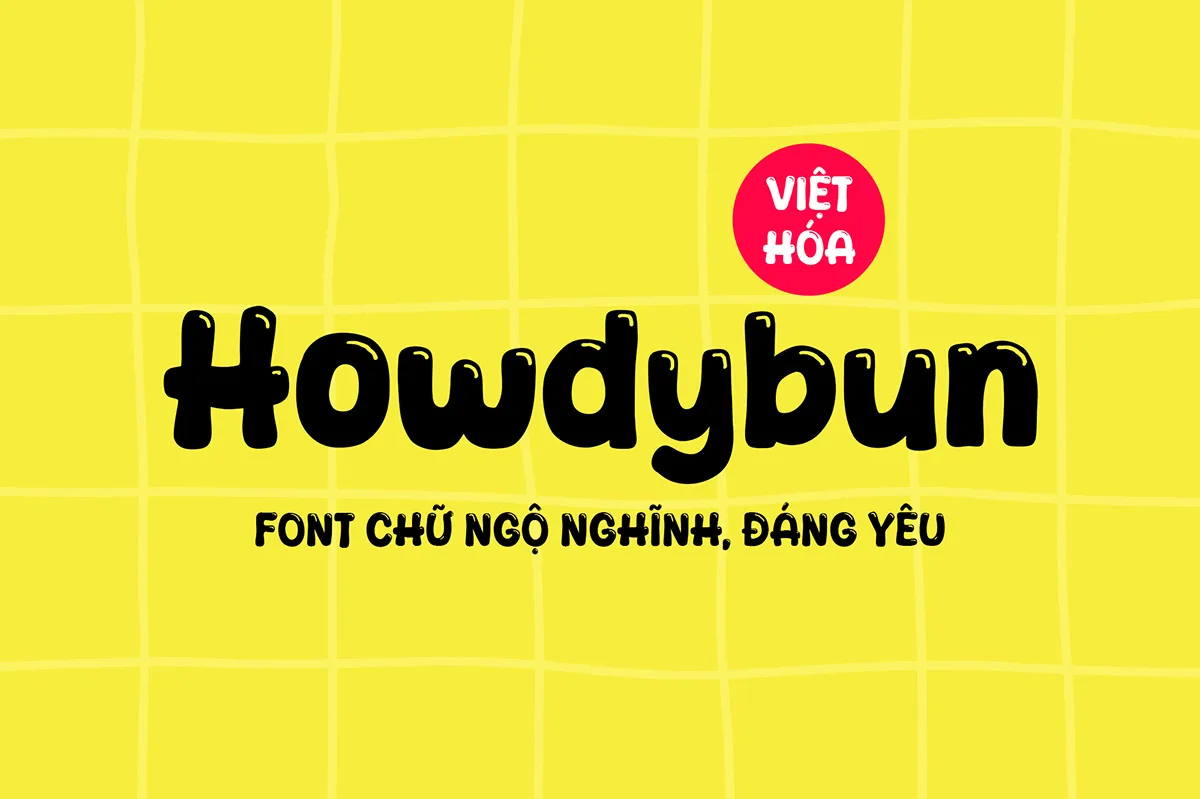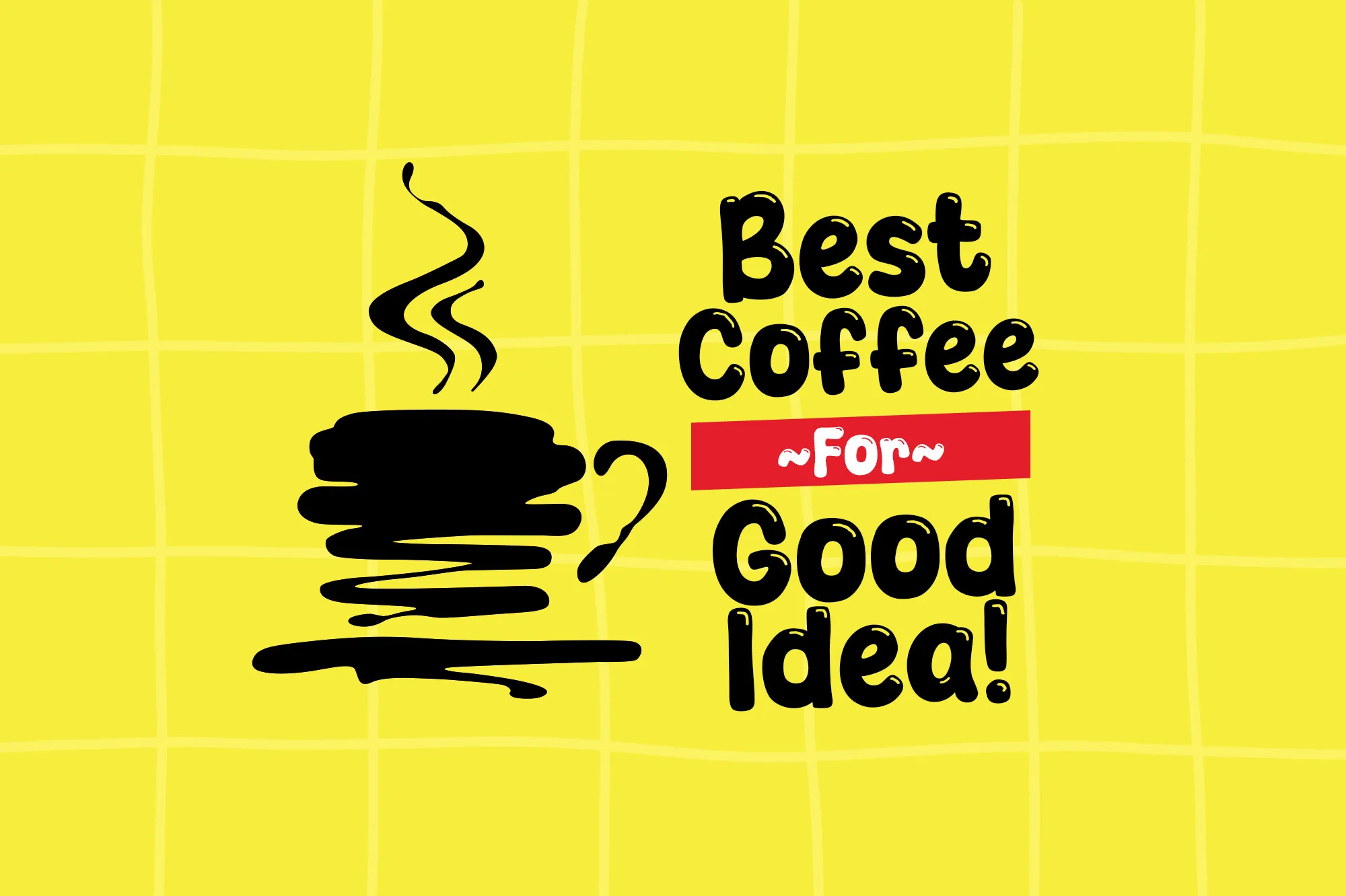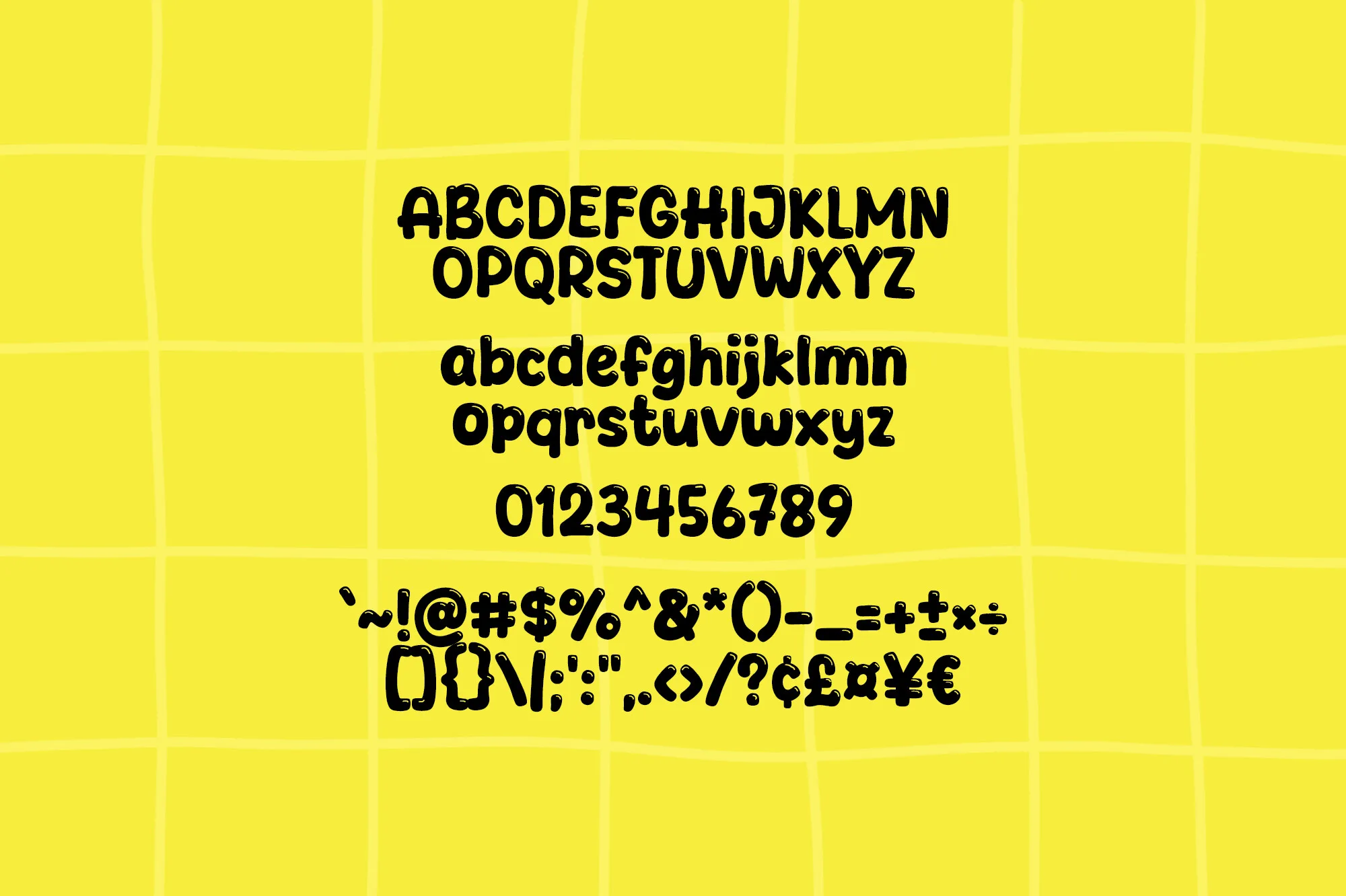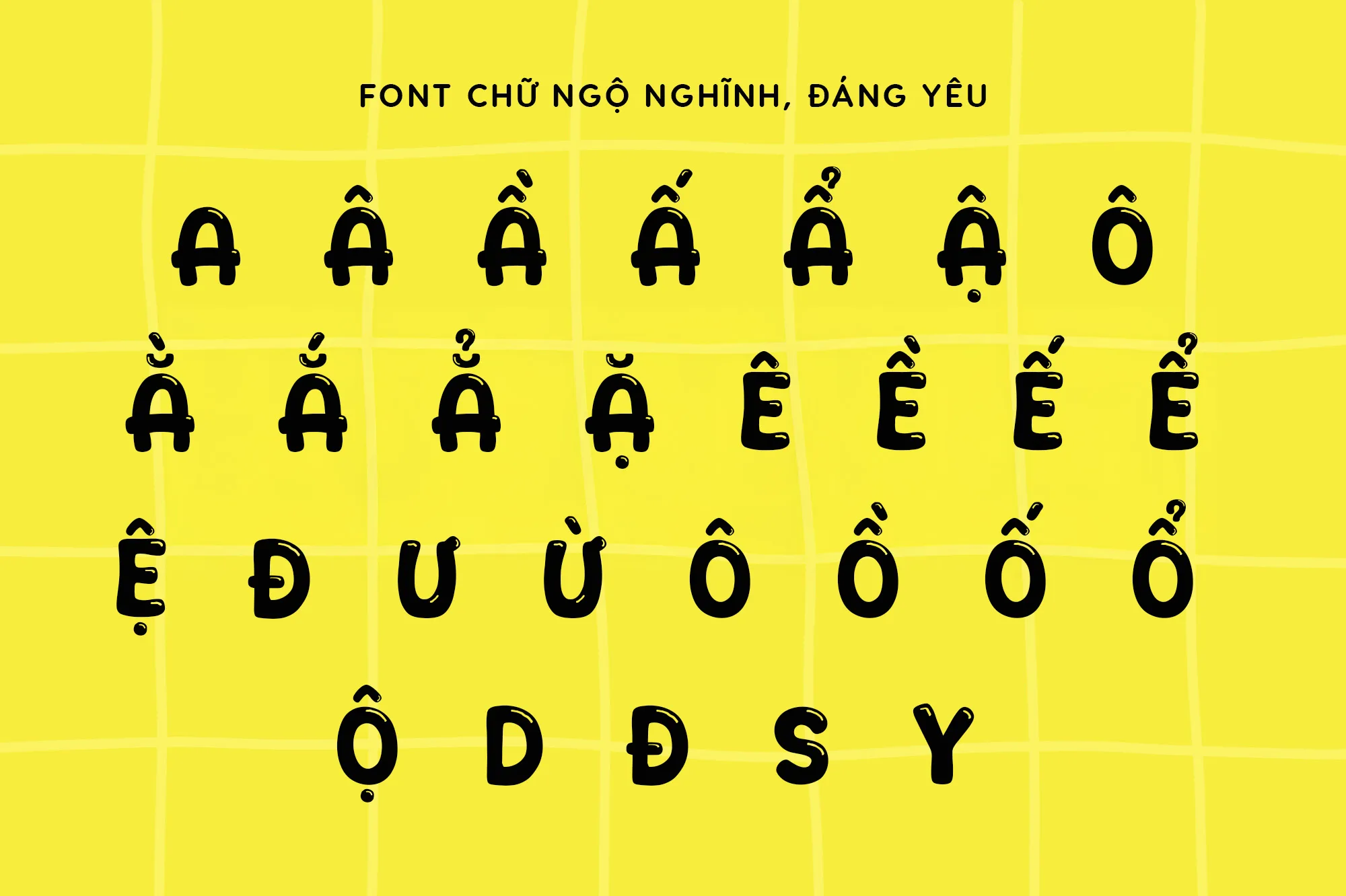
DVN – Howdybun Việt hóa – Font chữ đáng yêu, tròn trịa như chiếc bánh!
DVN Howdybun Việt hóa là một kiểu chữ ngộ nghĩnh, mềm mại và đậm chất vui tươi, lấy cảm hứng từ những chiếc bánh ngọt tròn xinh. Với các nét chữ bo cong, dày dặn và chi tiết nhỏ mô phỏng hiệu ứng “kem tan chảy” trên đầu mỗi ký tự, font này tạo cảm giác thân thiện và ấm áp ngay từ cái nhìn đầu tiên. Phù hợp hoàn hảo cho các thiết kế dành cho trẻ em, tiêu đề poster, bao bì sản phẩm dễ thương, hoặc dự án branding mang phong cách thân thiện, dễ gần. Bản Việt hóa đầy đủ hỗ trợ dấu tiếng Việt rõ ràng. Hãy thử ngay DVN Howdybun để thêm vị ngọt ngào và sự đáng yêu vào thiết kế của bạn!